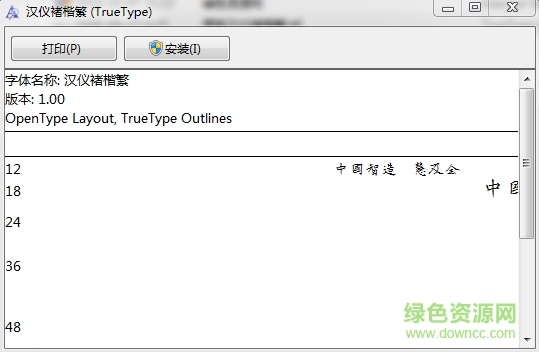
軟件介紹 軟件標(biāo)簽: 漢儀字體 字體 漢儀褚楷繁是一款很好用的電腦繁體字體,這種字體寫出來是真的很好看,有著自己獨(dú)特的風(fēng)格,不拘小節(jié),又大氣耐看,歡迎有需要這款字體的朋友來綠色資源網(wǎng)下載。安裝說明:第一種1.下載字體并解壓縮;2.開始中打開控制面板;3.在控制面板中打開字體文件夾;4.把下載的字體復(fù)制到此文件夾下;5.文字添加完成第二種1.下載字體并解壓縮;2.把文件根目錄下的字體壓縮包解壓縮;3.把文件根目錄下的安裝字體.bat放到含有字體文件的文件夾中,雙擊安裝字體.bat軟件;4.文字添加完成 本字體如果商用,請聯(lián)系漢儀字體官方獲得授權(quán)。 軟件截圖 上一張下一張(1 / 1) 安裝詳細(xì)截圖 其他版本下載 標(biāo)題 大小 更新日期 下載 下載地址 電腦版 漢儀褚楷繁 點(diǎn)擊報(bào)錯 軟件無法下載或下載后無法使用,請點(diǎn)擊報(bào)錯,謝謝! 關(guān)閉報(bào)錯反饋 請描述您所遇到的錯誤,我們將盡快予以修正,謝謝! *必填項(xiàng),請輸入內(nèi)容 本類最新 漢儀孟瑞體ttf v1.0 官方版 漢儀字庫免費(fèi) 132款 阿里巴巴普惠字體 官方ttf版 漢儀字體打包大全 for Mac 蘋果電腦版_ 共131款字體 漢儀純愛情書拼音體 ttf版 漢儀北魏寫經(jīng)w字體 免費(fèi)版 相關(guān)文章 Photoshop字體安裝使用方法和技巧 如何解決“無法新增字體”問題 Win 7系統(tǒng)安裝字體方法 網(wǎng)頁字體大小設(shè)置方法 怎么改網(wǎng)頁字體大小 在Linux系統(tǒng)中安裝字體的幾種方法 windows7字體顯示問題:打開某些程序的時(shí)候顯示的是亂碼 用戶評論 熱門評論 最新評論 發(fā)表評論 查看所有評論(0) 昵稱: 請不要評論無意義或臟話,我們所有評論會有人工審核. 字?jǐn)?shù): 0/500 (您的評論需要經(jīng)過審核才能顯示)